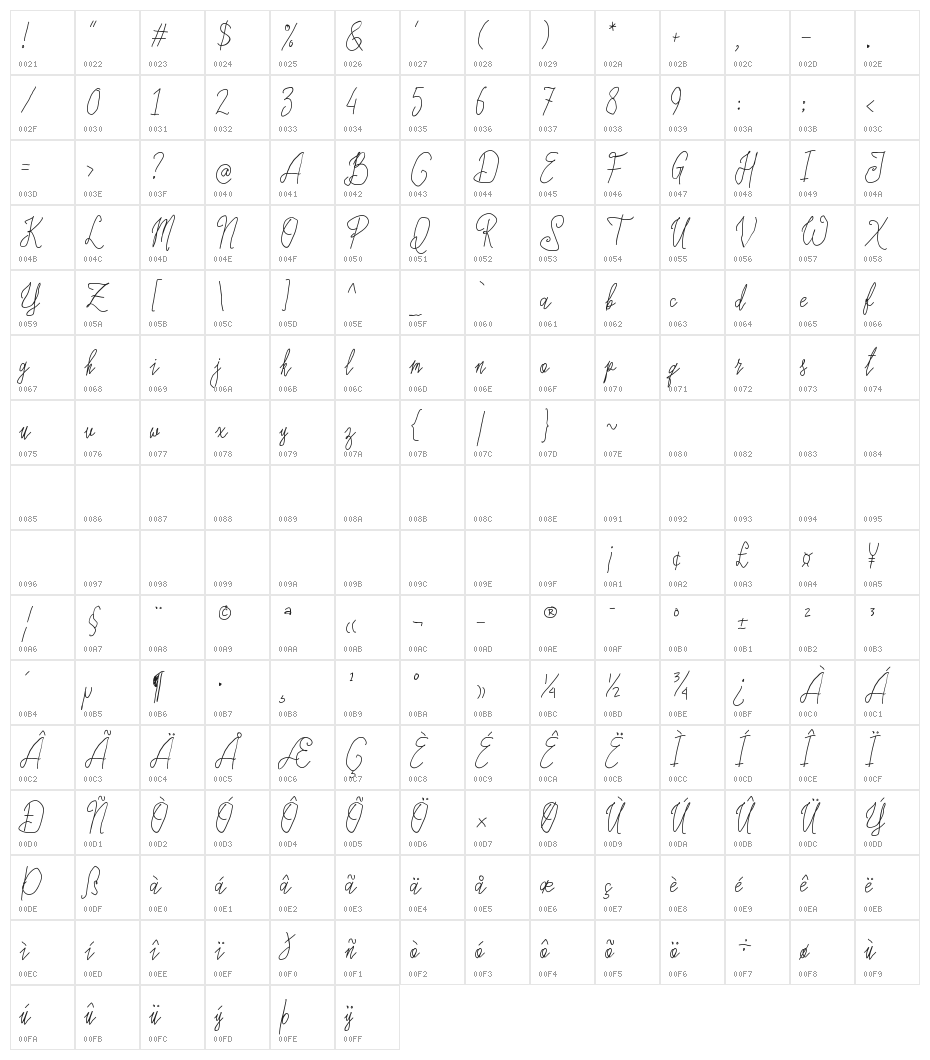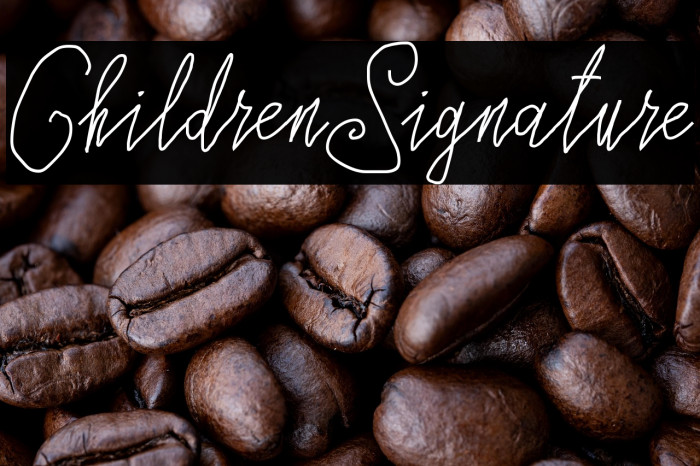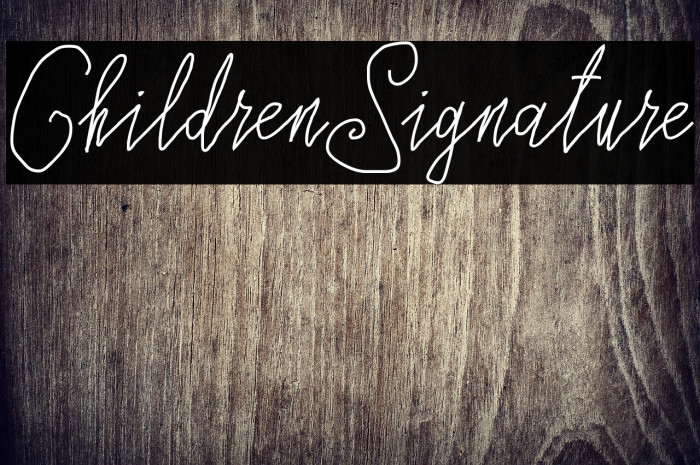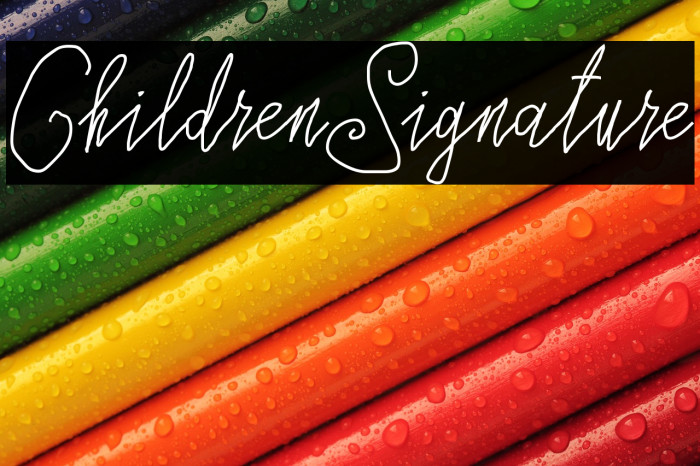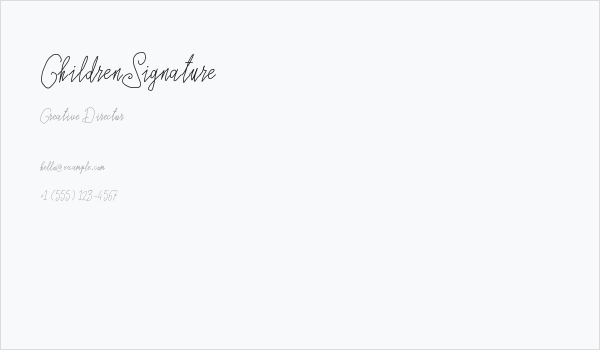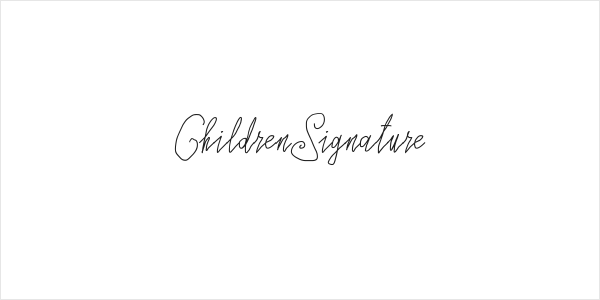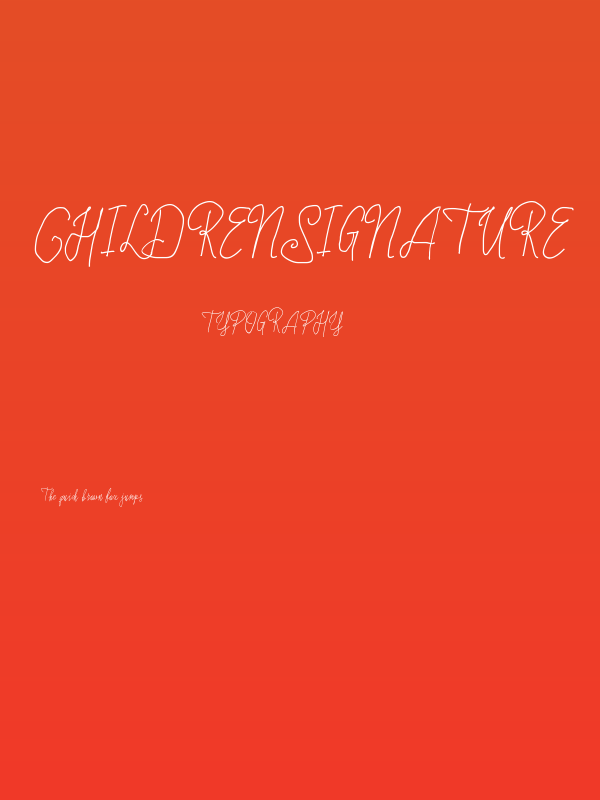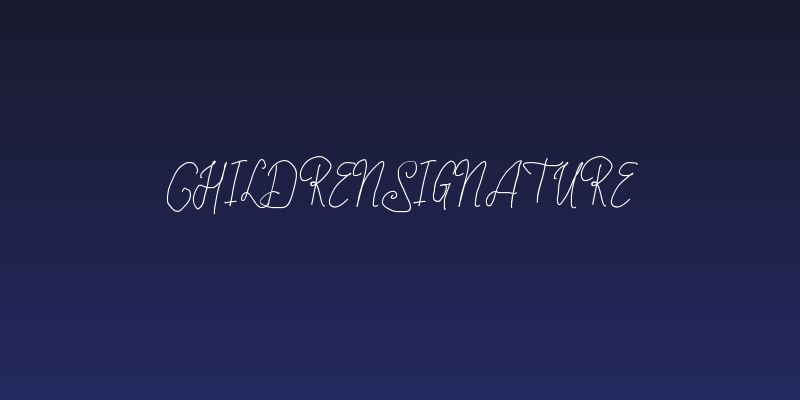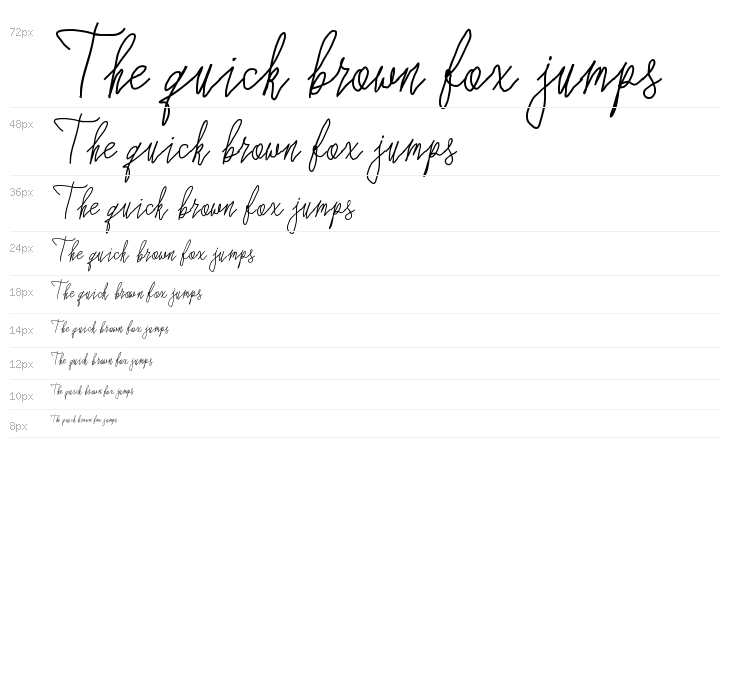
ChildrenSignature Font
| Stile generale | Playful, Whimsical |
| Caso d'uso | Headlines, Creative projects, Invitations |
| Progetti proposti | Ideal for children's book covers, playful invitations, greeting cards, and creative branding projects. |